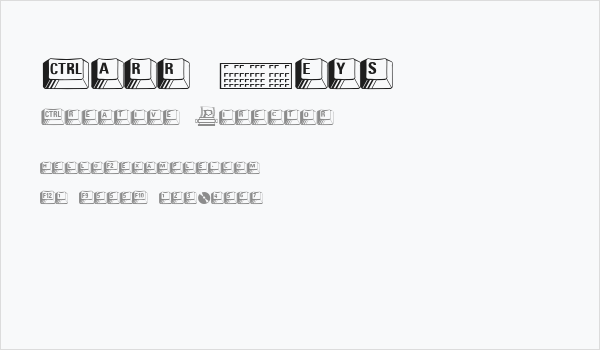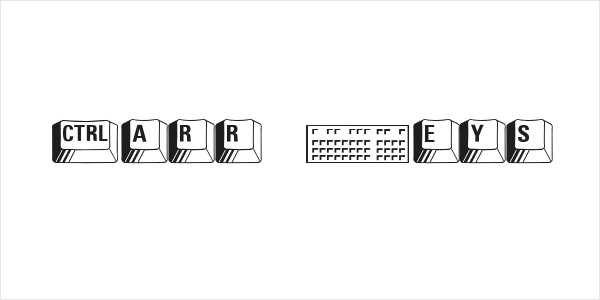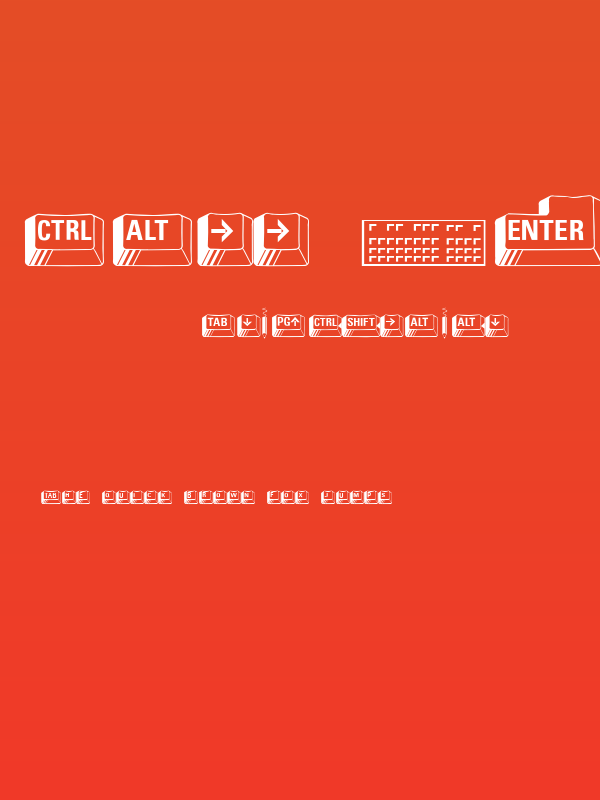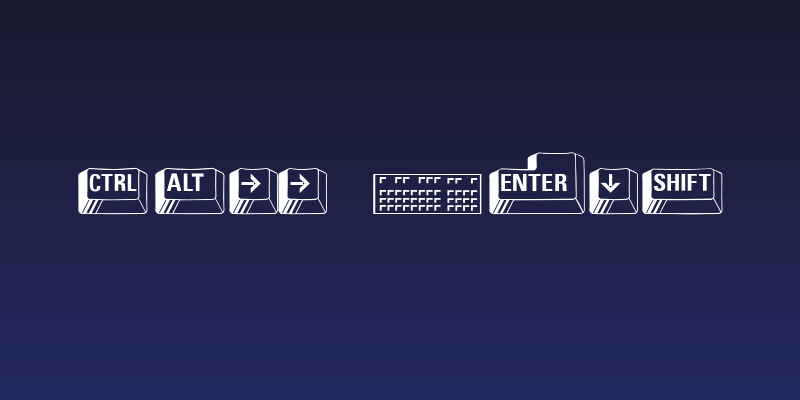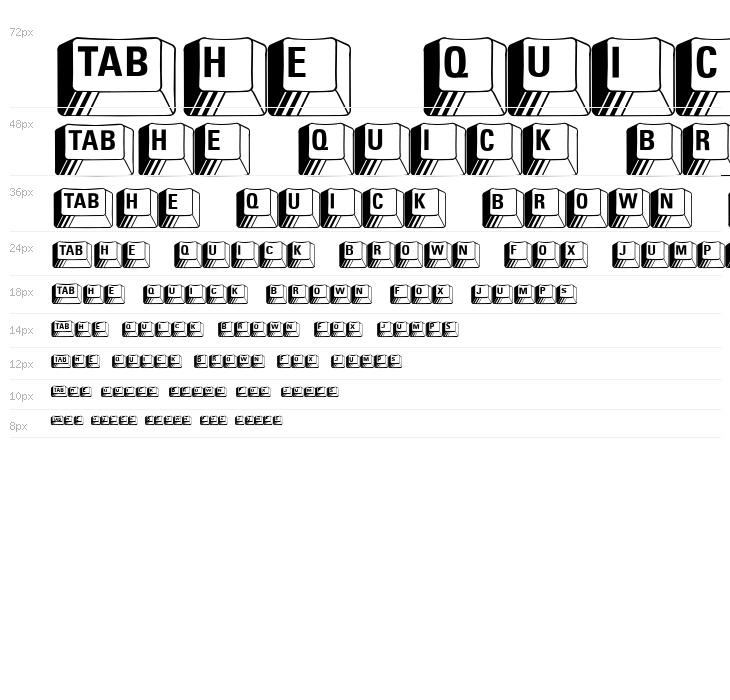
Carr Keys Font
| Caso d'uso | Logos, Posters, Themed Events |
| Progetti proposti | Ideal for retro-themed designs, tech-related branding, or educational materials about the history of computing. |